Schriftgarnitur
»Schriftgarnitur« ist ein typografischer Fachausdruck aus dem gewerbespezifischen Sprachschatz dspr. Schriftsetzer, Schriftgießer und Drucker aus der Periode des materiellen Schriftsatzes mit physischen Drucktypen aus Metall (z.B. aus einer Blei-Zinn-Antimon-Kupfer-Legierung), Holz (z.B. aus Birnenholz) oder Kunststoff (z.B. aus Kunstharz) für ein Ensemble aller verfügbarer Kegelgrößen eines Schriftschnitts; alle verfügbaren physischen Schriftgrade einer Schriftstilvariante einer Schriftfamilie. 1)
Etymologisch leitet sich »Garnitur« von von frz. »garniture« für »Ausrüstung« bzw. »Ausstattung« (»garnieren« von frz. »garnir«) ab. Unter einer »Garnitur« wird also eine »komplette Ausrüstung« verstanden.
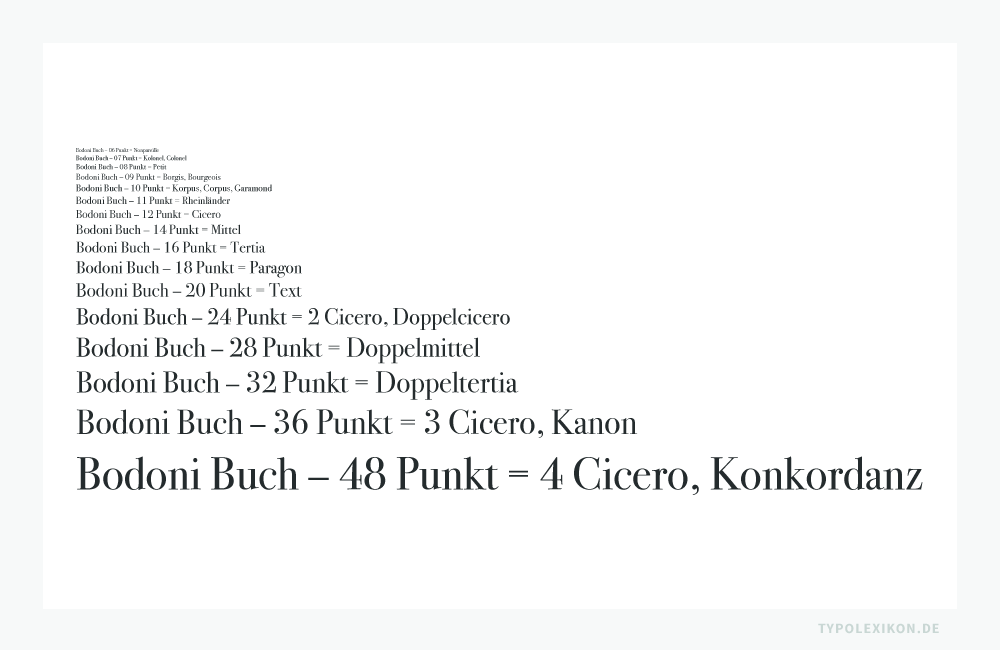
Laut dem deutschen Typografen Paul Renner (1878–1956) war u.a. jeweils die Schriftstilvariante »steil«, »schräg«, »mager«, »halbfett«, »dreiviertelfett«, »schmal« oder »breit« je eine Garnitur einer Schrift. 2)
Beispielsweise zählte der »normale« Schnitt der Bleisatzschrift »Bauer Bodoni« von Heinrich Jost (1889–1948) in allen verfügbaren physischen Schriftgraden als eine Schriftgarnitur. Fertigte und verkaufte die »Bauersche Gießerei« (Font Foundry) dann auch noch zusätzlich einen »kursiven« Schnitt in unterschiedlichen Schriftgraden, galt dieser als eine separate »Garnitur« der Bauer Bodoni. Verfügte eine Druckerei über einen normalen, kursiven und fetten Schnitt, besaß sie folglich drei Garnituren der Bauer Bodoni.
Eine vollständige Schriftgarnitur für den Werksatz umfasste in der Regel die Mittel (Mittelname) Nonpareille bis 4 Cicero, also 6 bis 48 Didot-Punkte (Typografischer Punkt). Qualitativ hochwertige und gut ausgebaute Schriftgarnituren verfügten in den jeweiligen Optischen Größen über unterschiedliche Letternarchitekturen (Typometrien), also über speziell gestaltete Konsultationsgrößen, Lesegrößen, Schaugrößen und Plakat– bzw. Ferngrößen sowie unterschiedliche Breitenläufe (z.B. eng, normal, weit oder extraweit).
Je mehr und je besser ausgebaute Schriftgarnituren eine Offizin vorrätig hatte, desto mehr bzw. größere Depots benötigte sie für die Aufbewahrung ihrer tonnenschweren Drucktypen. 3)
| ↑1 | Quelle: Bosshard, Hans Rudolf: Technische Grundlagen zur Satzherstellung, Bildungsverband Schweizer Typografen, Bern, 1980, Seite 159, ISBN: 3855840105 und 3-85584-010-5. |
| ↑2 | Anmerkung: Gemeint ist damit die jeweilige Strichstärke, Schriftbreite, Schriftlage bzw. Zierform einer Schrift. Quelle: Renner, Paul: Die Kunst der Typografie (1949), Maro Verlag Augsburg, 2003, Seite 242, ISBN: 9783875124149. |
| ↑3 | Anmerkung: Insbesondere die enormen Lagerkosten von tonnenschweren Schriftgarnituren führten dazu, weshalb im Handsatz nur sehr wenig unterschiedliche Werksatzschriften von den Offizinen bzw. Druckereien genutzt wurden. Daher rührt auch die prominente Binsenweisheit, dass man nur wenige Schriften braucht, um gute Typografie zu machen. Was allerdings schlussendlich dazu führte, dass alle für alles die gleichen Schriften verwendeten, z.B. die »Times«, die »Garamond« oder die »Helvetica«. |